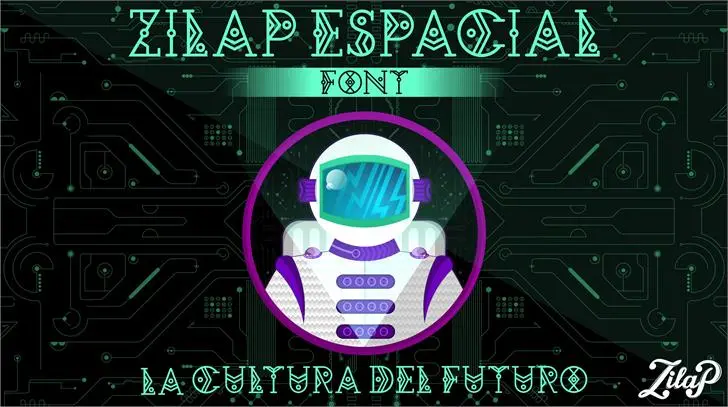
A fonte Zilap Espacial é uma criação visionária inspirada no espírito futurista do cosmos, perfeitamente adequada para qualquer projeto que busque expressar conceitos relacionados à astronomia ou tecnologia espacial. Suas linhas diretas e suas formas abstratas fazem dela uma opção ideal para designers que querem transmitir um sentimento de aventura espacial e inovação, seja na criação de logotipos de empresas espaciais, capa de livros sobre astronomia ou até mesmo em gráficos publicitários promovendo viagens interplanetárias. Inspirada no desapego pelo espaço, a Zilap Espacial atua como uma aliada perfeita para quem busca incorporar um toque único e emocionante ao seu trabalho.